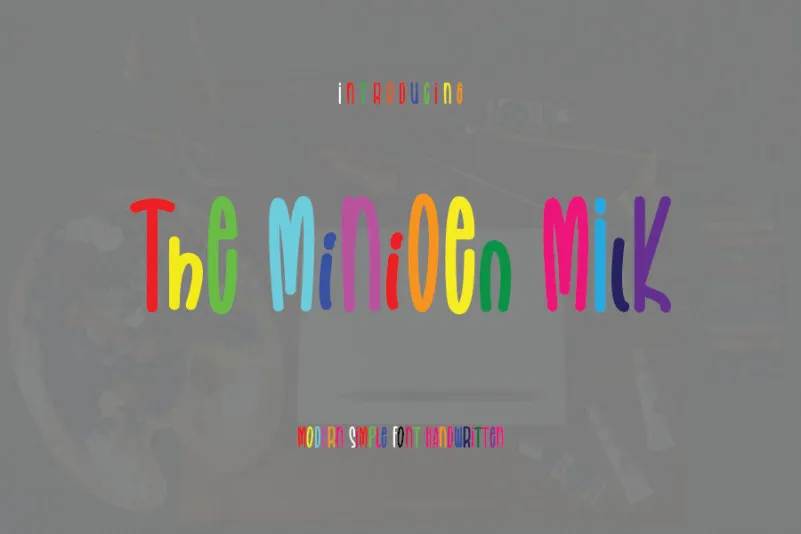
The Minioen Milk Font – Download Grátis
A fonte “The Minioen Milk” é uma tipografia escrita a mão que transmite sofisticação e elegância, com uma escrita bem equilibrada e refinada. Inspirada em scripts estilizados, esta font oferece alternativas estilizadas e ligaturas perfeitas para complementar projetos de qualquer tipo. Ela é o ideal companheiro para gráficos profissionais, design de logotipos, ou até mesmo para criação de ilustrações delicadas que exalam um toque romântico e elegante. Seja você designer de moda, arquiteto ou ilustrador, a font “The Minioen Milk” é uma escolha perfeita para dar vida ao seu projeto através da sua escrita única e sofisticada. Download agora e adicione um toque autêntico à sua próxima criação visual.
Designer: handwrittenwanda